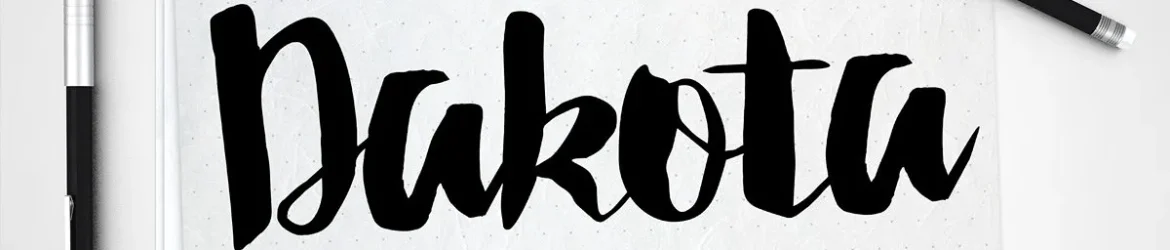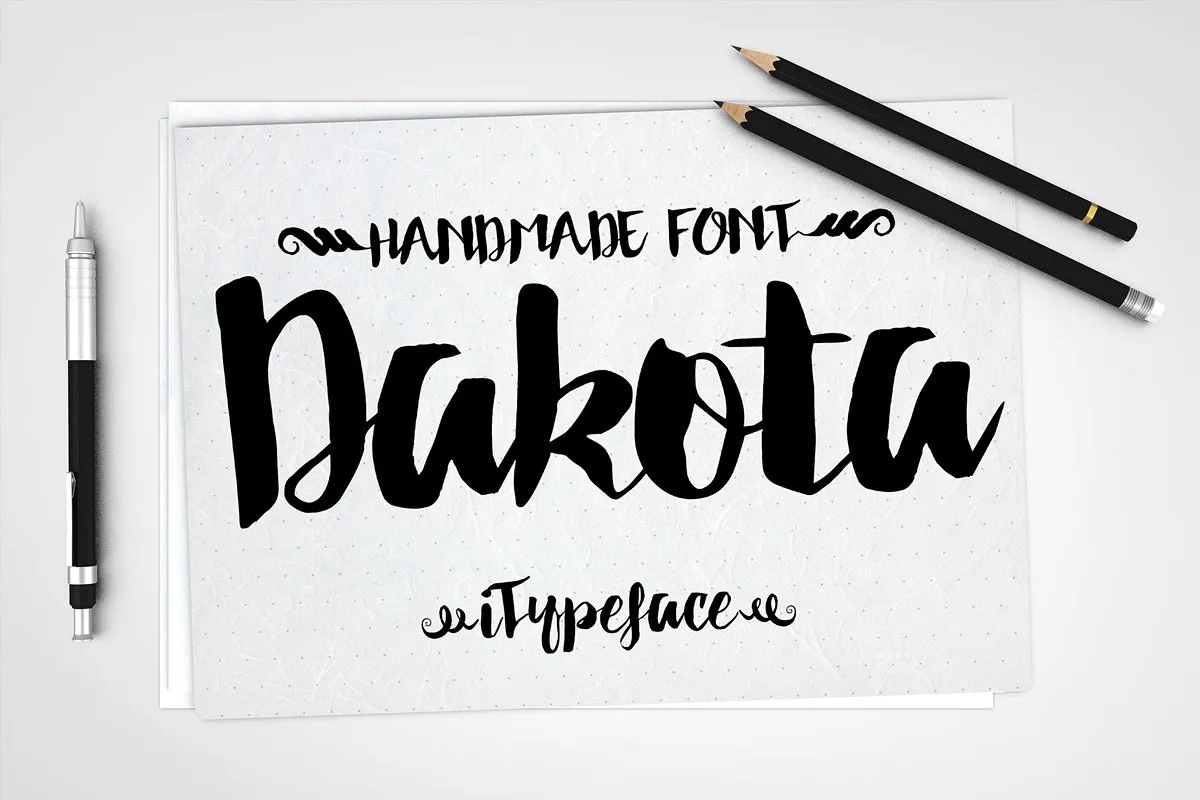
Dakota Script Font
A Dakota Script Font é uma tipografia moderna que traz a elegância do traçado à sua arte digital. Sua design foi criado pelo designer Hamilton para criar um efeito fluído e vibrante, ideal para expressar sentimentos emotivos. Perfeita para aplicação em design de convites de casamento, cartões de cumprimentos ou qualquer elemento que busque uma sensação natural e autêntica para se destacar. A Dakota Script é perfeitamente adaptada à estética das cores e texturas do desenho a mão livre, trazendo vida e movimento à sua obra, tornando-a um recurso imprescindível para qualquer designer gráfico que procura manter uma ligação sólida com o universo dos materiais tradicionais.